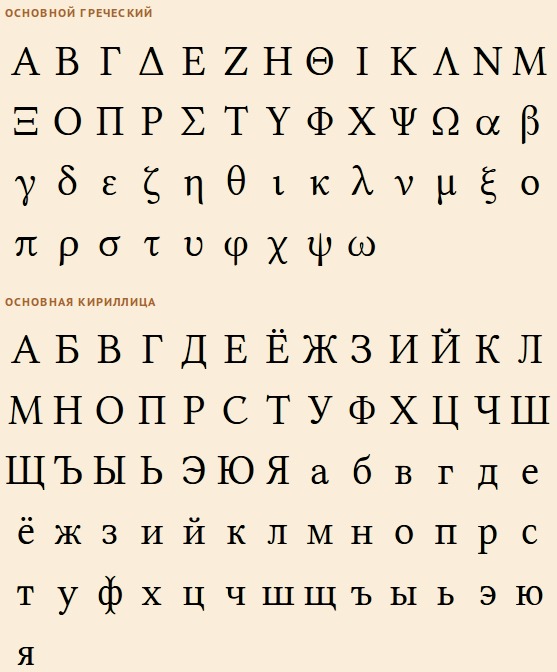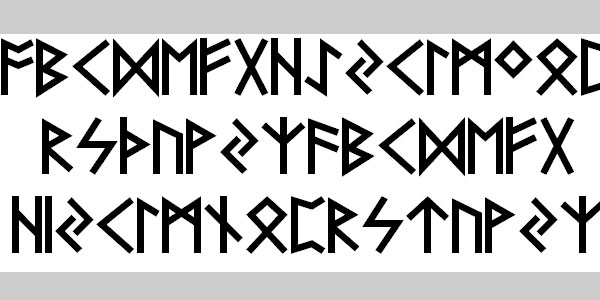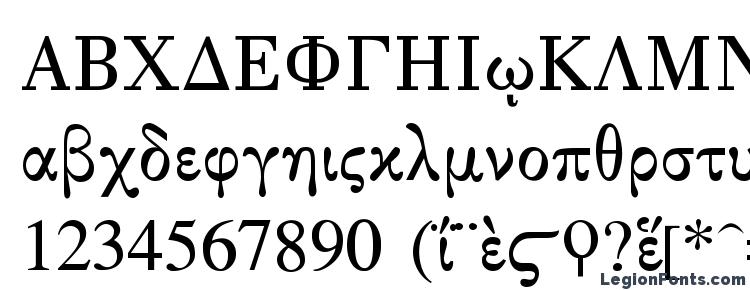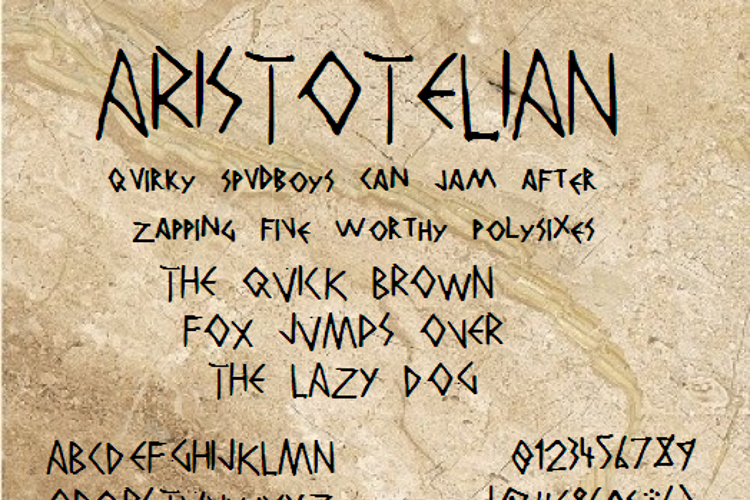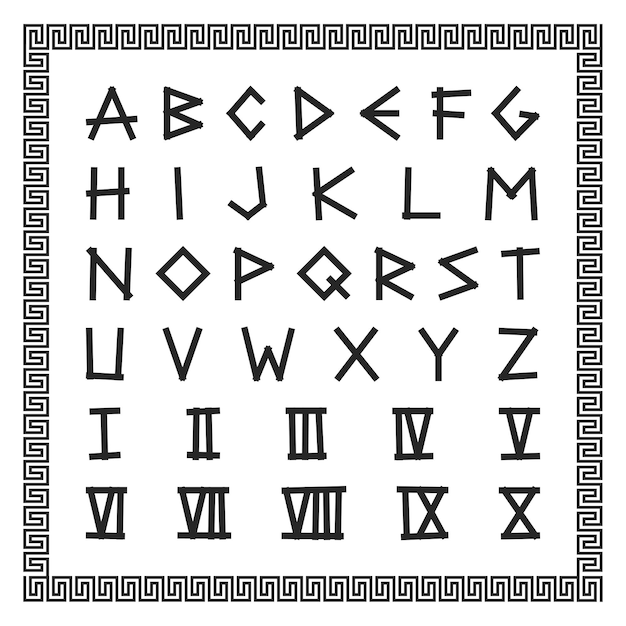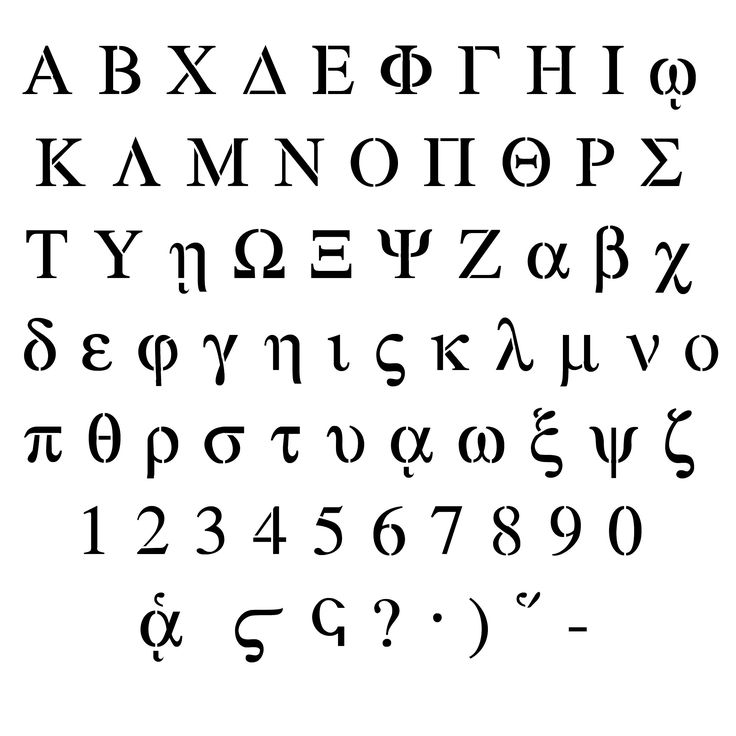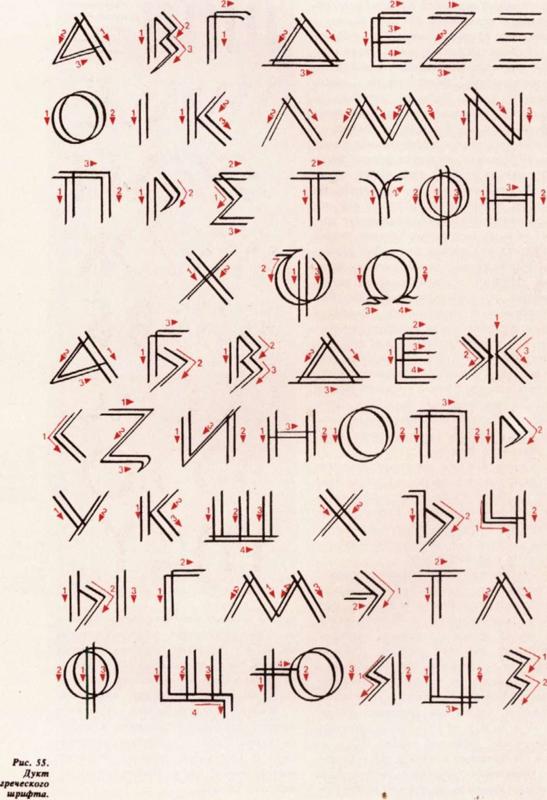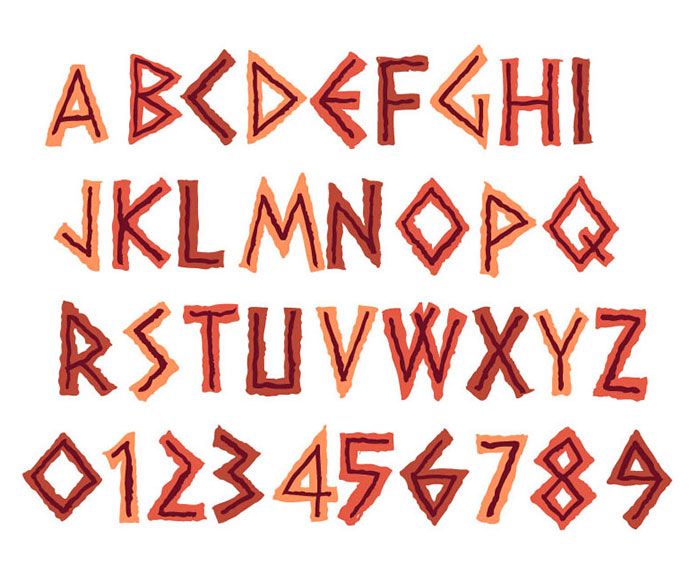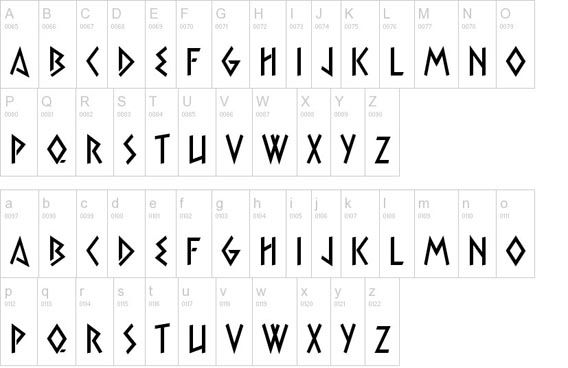
Шрифт греческий стиль: Коллекция греческих шрифтов с поддержкой кириллицы
29. Греческий шрифт мин.
Из Cat Made Pattern этот шрифт придаст вашему проекту древнегреческую атмосферу.
30. Tavernaki min
Этот шрифт поддерживает латинские и греческие символы, если вашему проекту нужен гладкий рукописный вид.
31. Шрифт Millennium Blackletter мин.